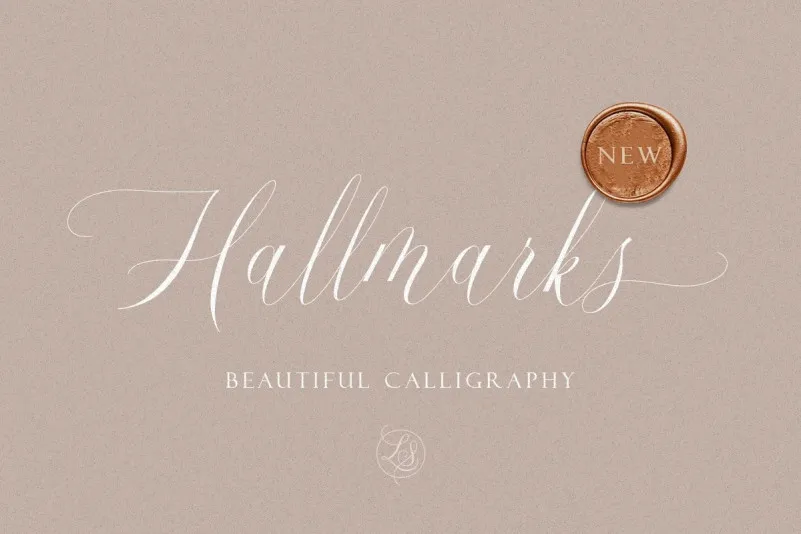
A Hallmarks Font é uma excelente escolha para aqueles que buscam um estilo delicado e elegante em seus projetos. Criada com base em uma escrita a mão, esta fonte foi projetada para parecer mais próxima possível de uma escrita natural. Perfeita para uso em cartões de casamento, frases ilustrativas, marcas de marca ou embalagens, ela adicionará um toque suave e sofisticado aos seus designs. Esta fonte não é apenas uma opção para quem busca uma sensação mais feminina, mas também serve como uma ótima escolha para qualquer projeto que valorize elegância e delicadeza. Experimente Hallmarks Font na sua próxima criação e faça um diferencial com um toque natural e sofisticado em seus designs.